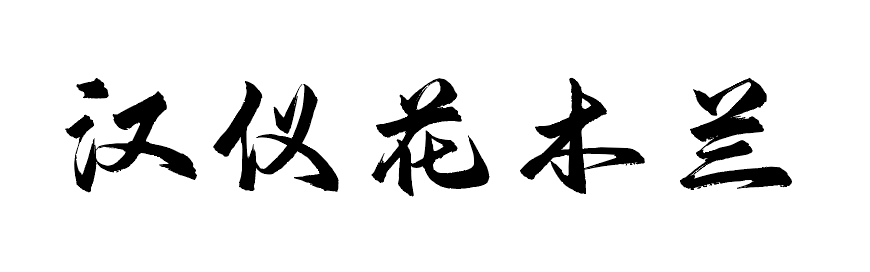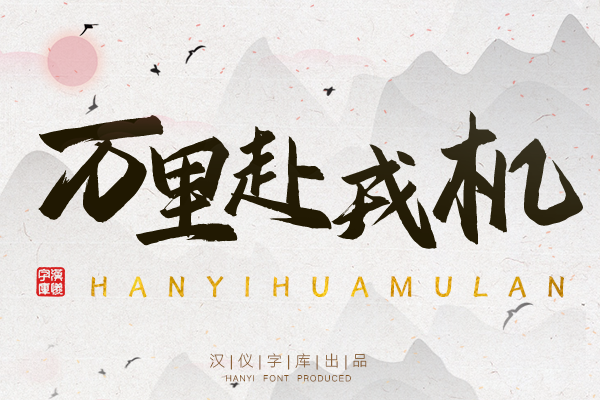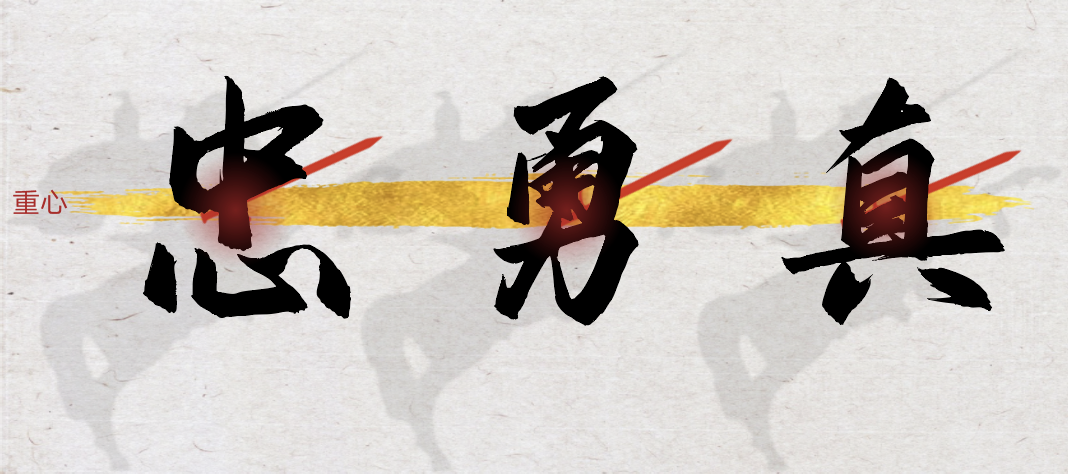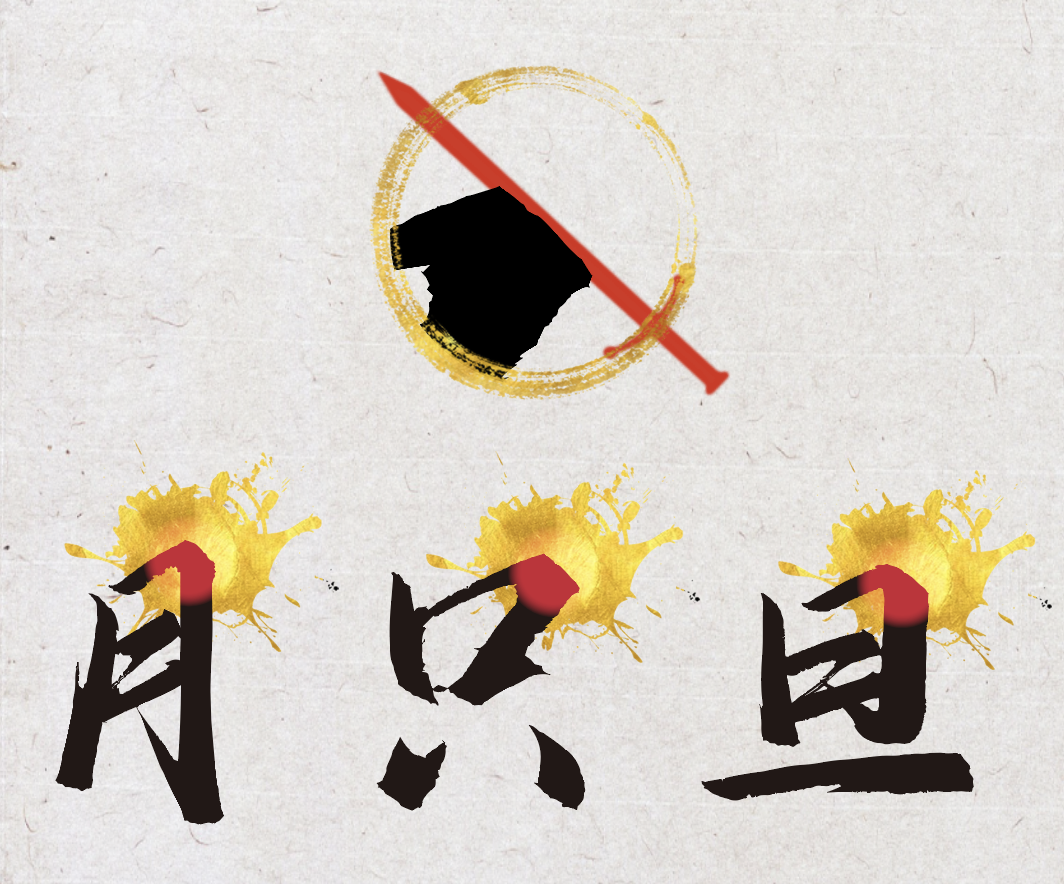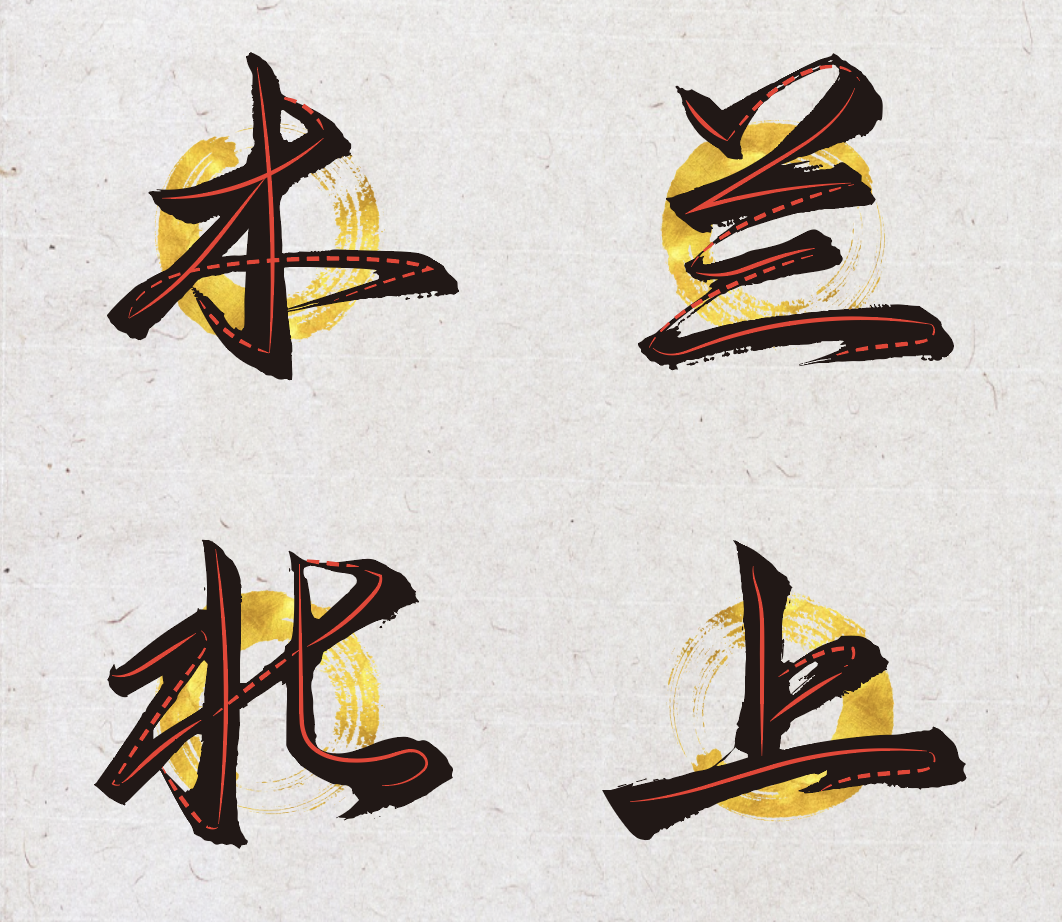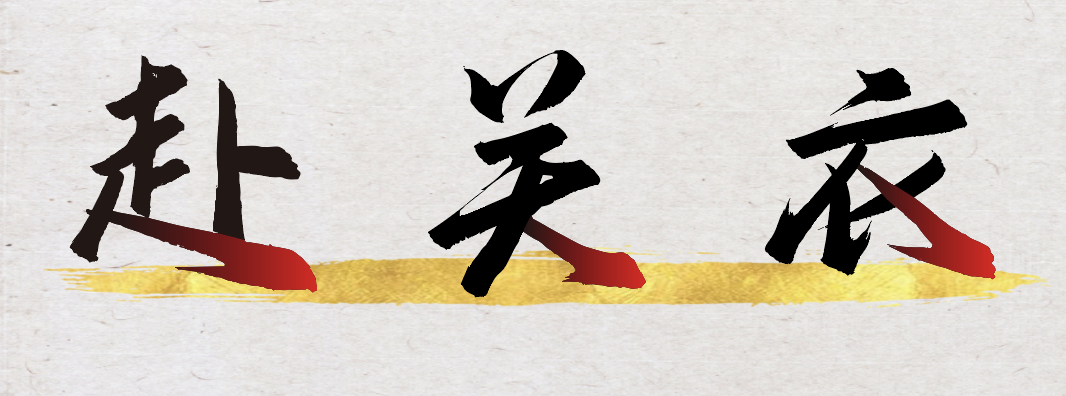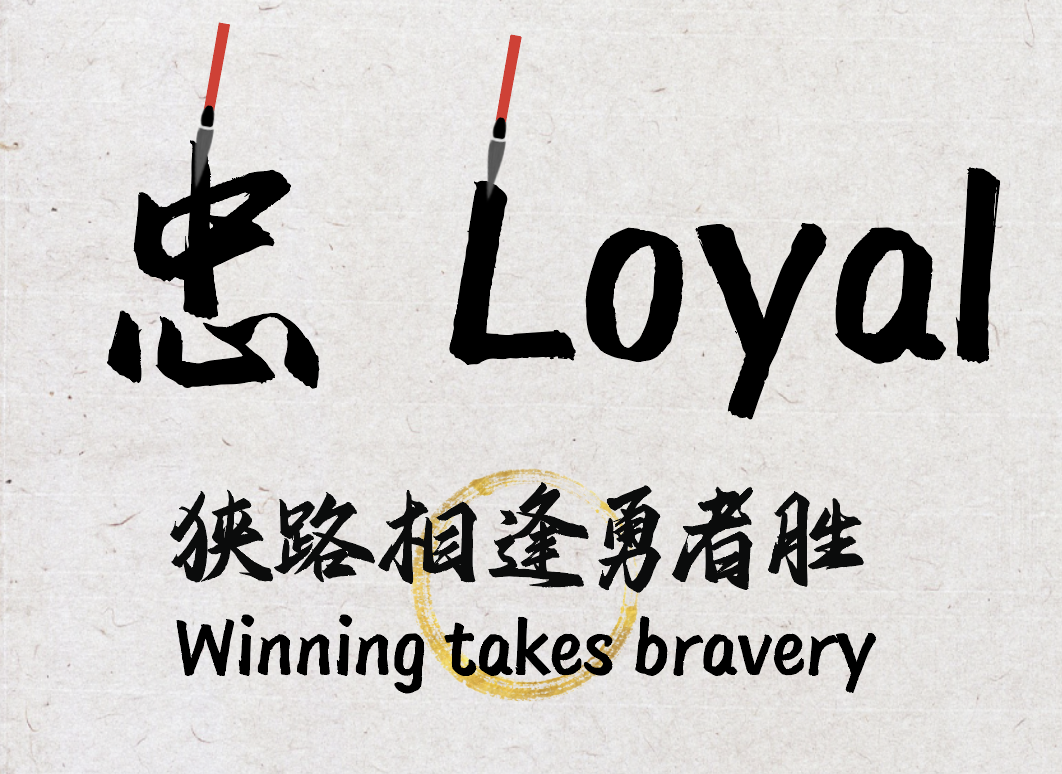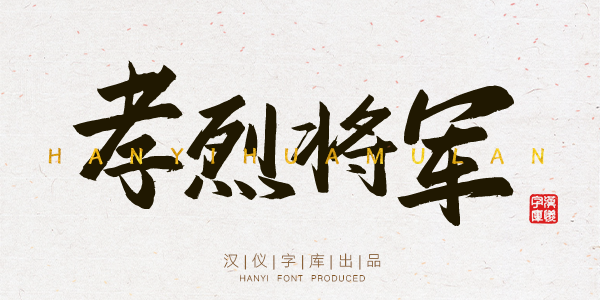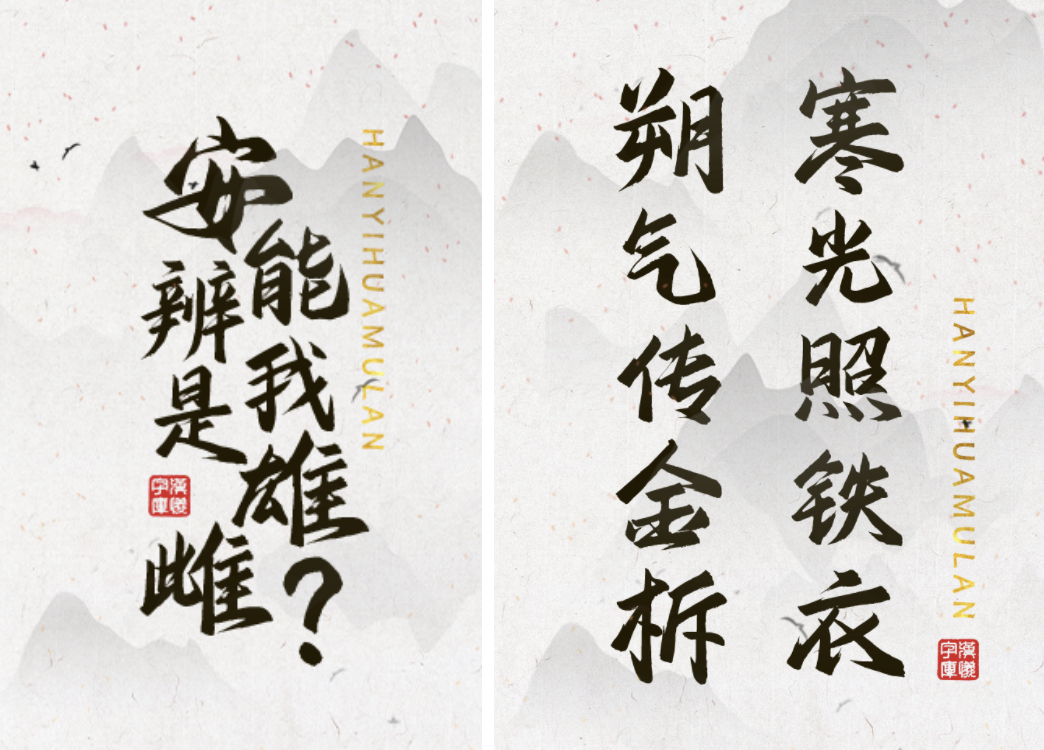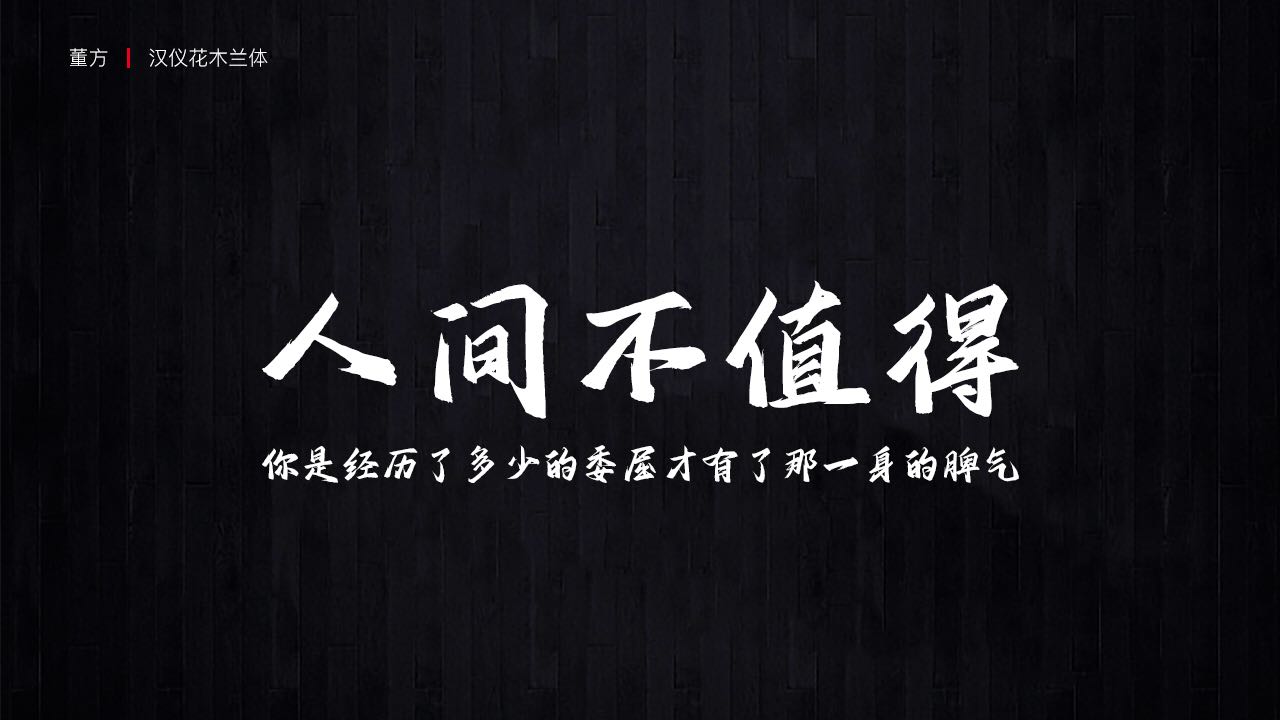
汉仪花木兰字体介绍,一款有着英勇无畏精神的字体
汉仪花木兰 | 女中豪杰
“汉仪花木兰”是一款有着英勇无畏精神的字体,它的字迹潇洒飞扬,笔触丰富细腻。既有“弯弓征战作男儿”的英雄气概,又有“不教胡马度阴山”的热血豪情。
汉仪花木兰 | 整体气势统一
“汉仪花木兰”的整体态势略向右上方倾斜,与水平方向形成一定倾角,字形气势整齐统一。一个披枪跃马、快意扬鞭、戎装戍边、栩栩如生的巾帼形象瞬间跃然眼前。
汉仪花木兰 | 转折英姿飒爽
“汉仪花木兰”的笔画转折处简洁、果断而有力量。折肩展现出了字体英姿飒爽的性格形象。
汉仪花木兰 | 连笔刀光剑影
“汉仪花木兰”的运笔潇洒,连贯自如,书写出了如刀光剑影般的飞白效果。
汉仪花木兰 | 结构内敛沉稳
“汉仪花木兰”的笔画线条充满韧劲,收笔停顿再回锋,有一种“克敌垂成不受勋,凌然巾帼是将军”的稳重感。
汉仪花木兰 | 中西文匹配
“汉仪花木兰”的西文同样用毛笔书写,融入了中文书法的手写方式。笔触丰富,运笔流畅,手写感强,中西文的搭配和谐统一。
汉仪花木兰 | 排版效果